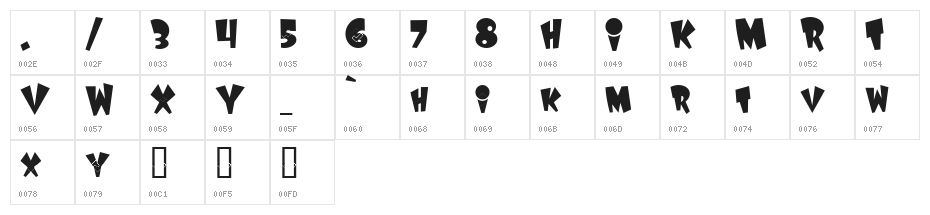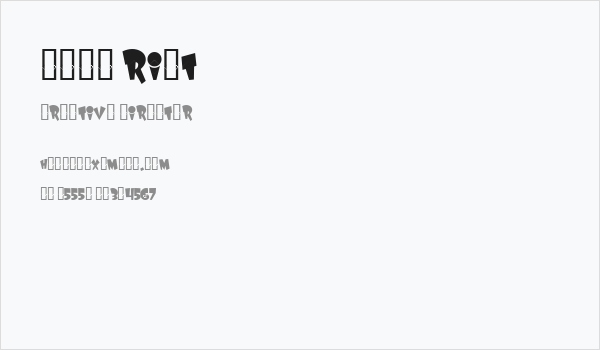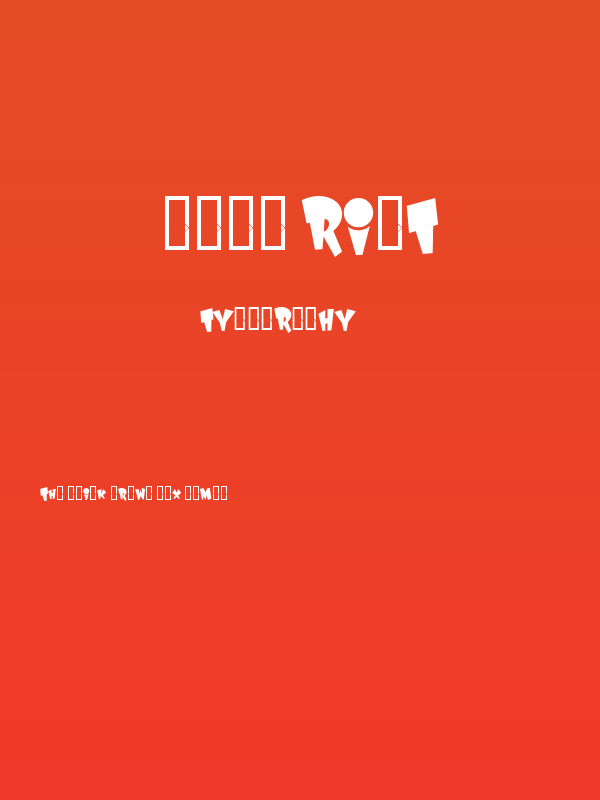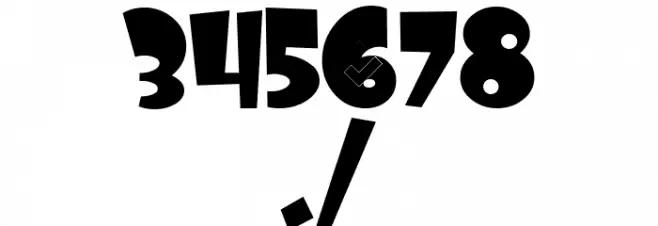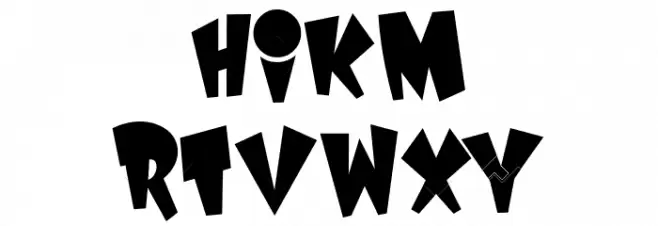
Laff Riot Font
| कंट्रास्ट | High |
| समग्र शैली | Playful, Cartoonish |
| उपयोग का मामला | Headlines, Logos, Posters |
| सुझाए गए प्रोजेक्ट | Ideal for children's books, comic strips, party invitations, and playful branding projects. |